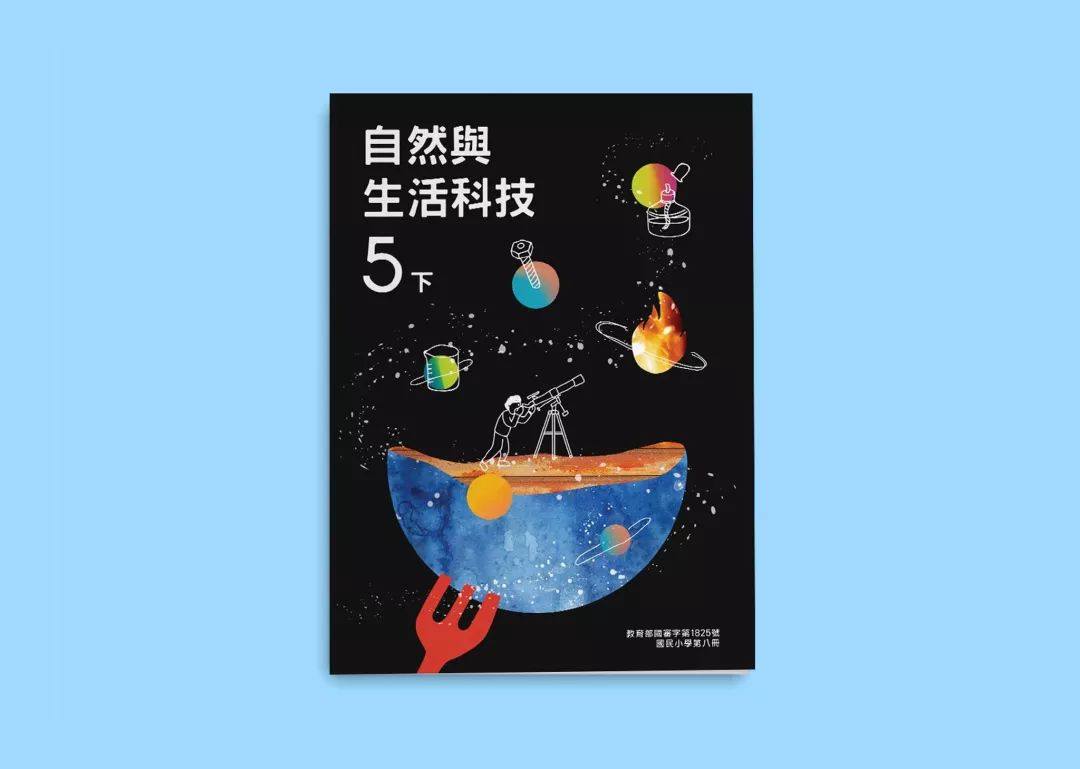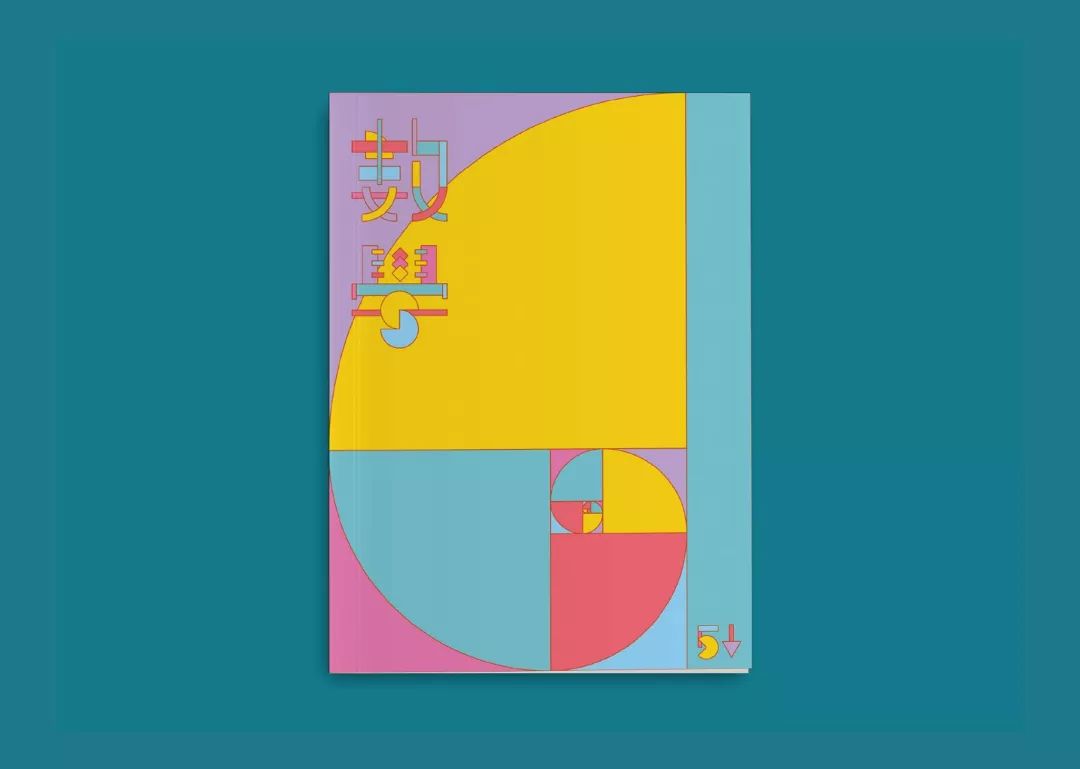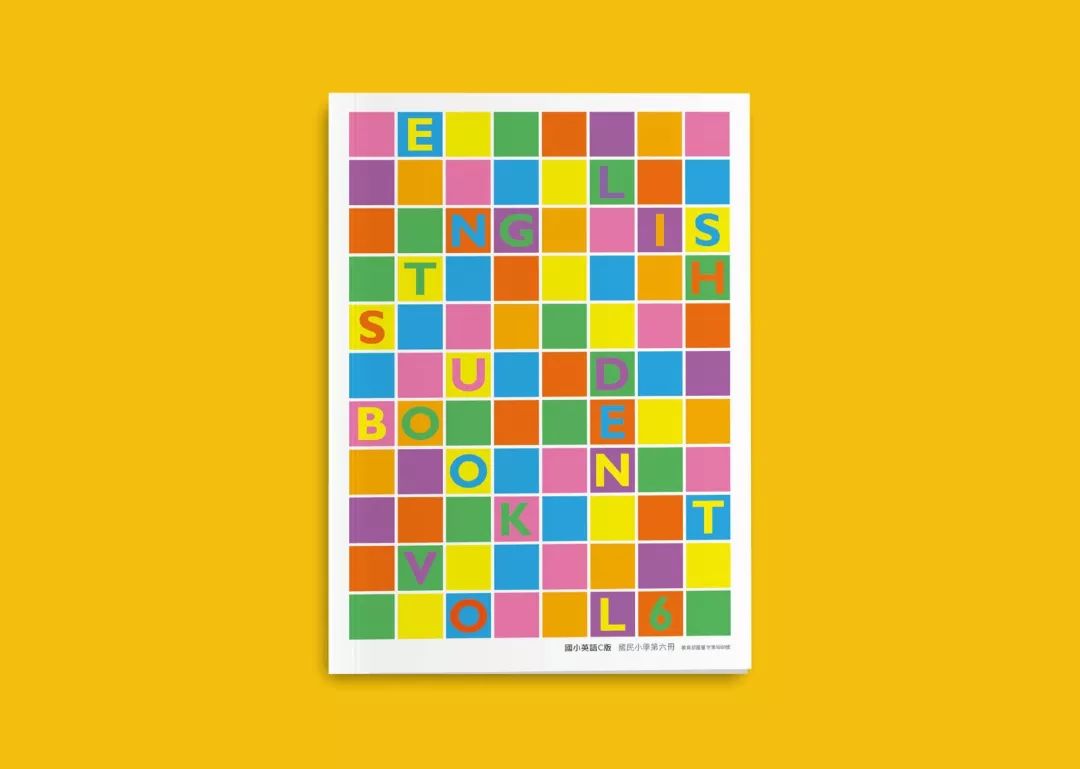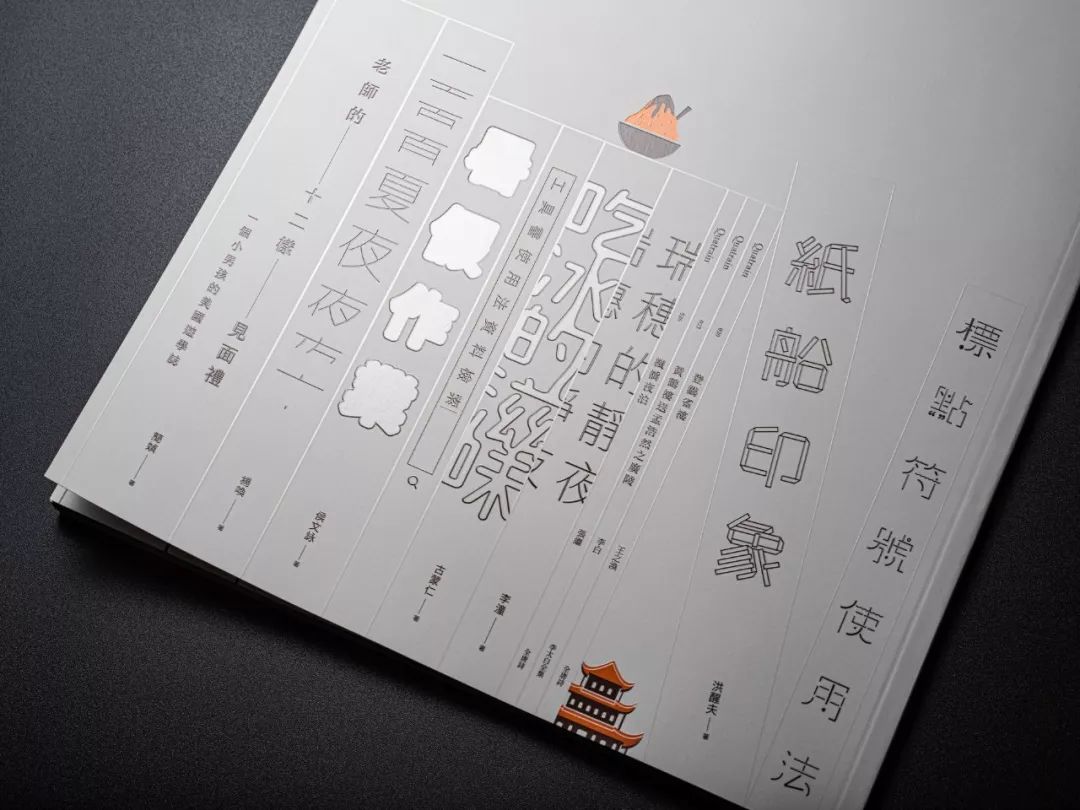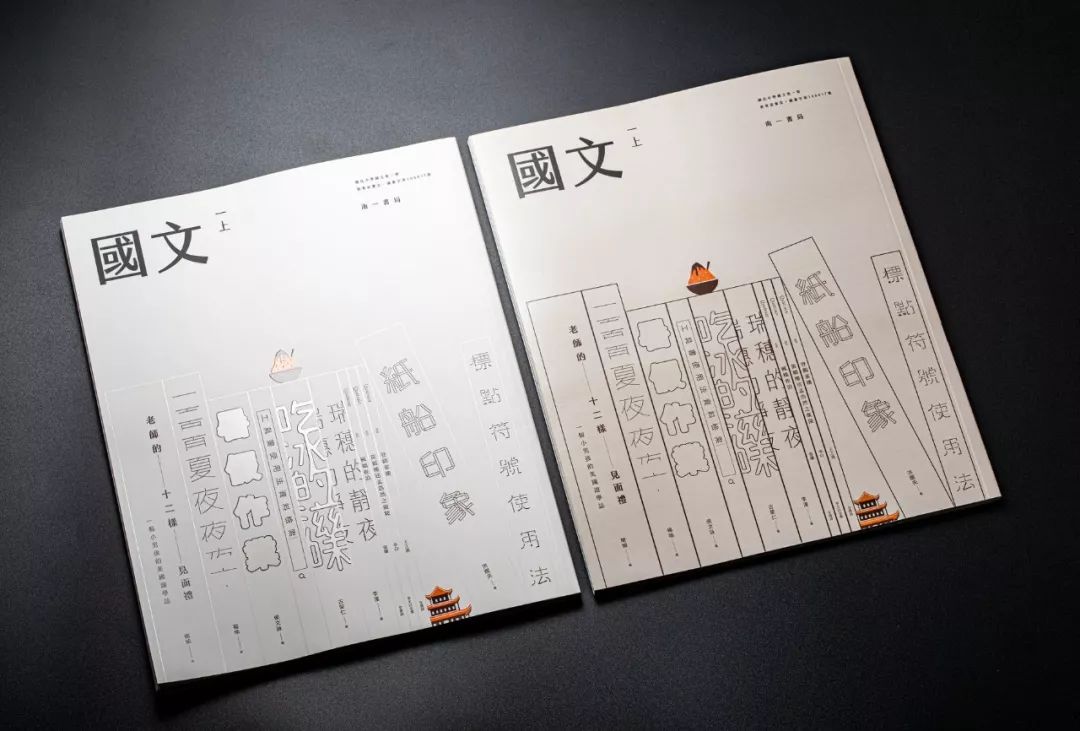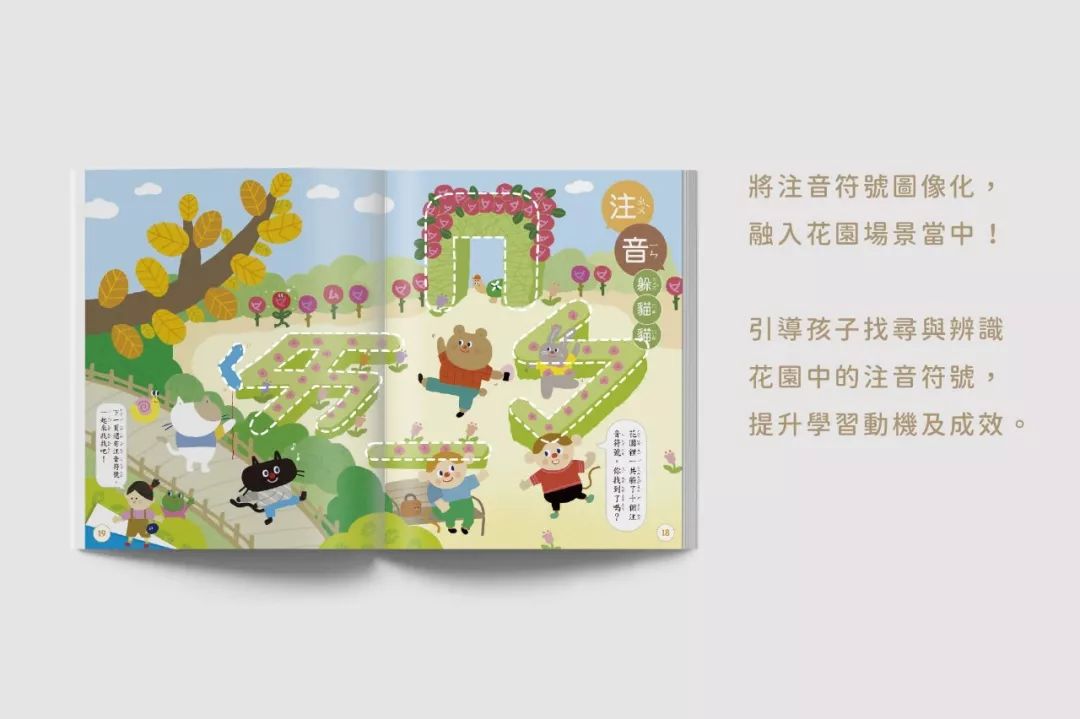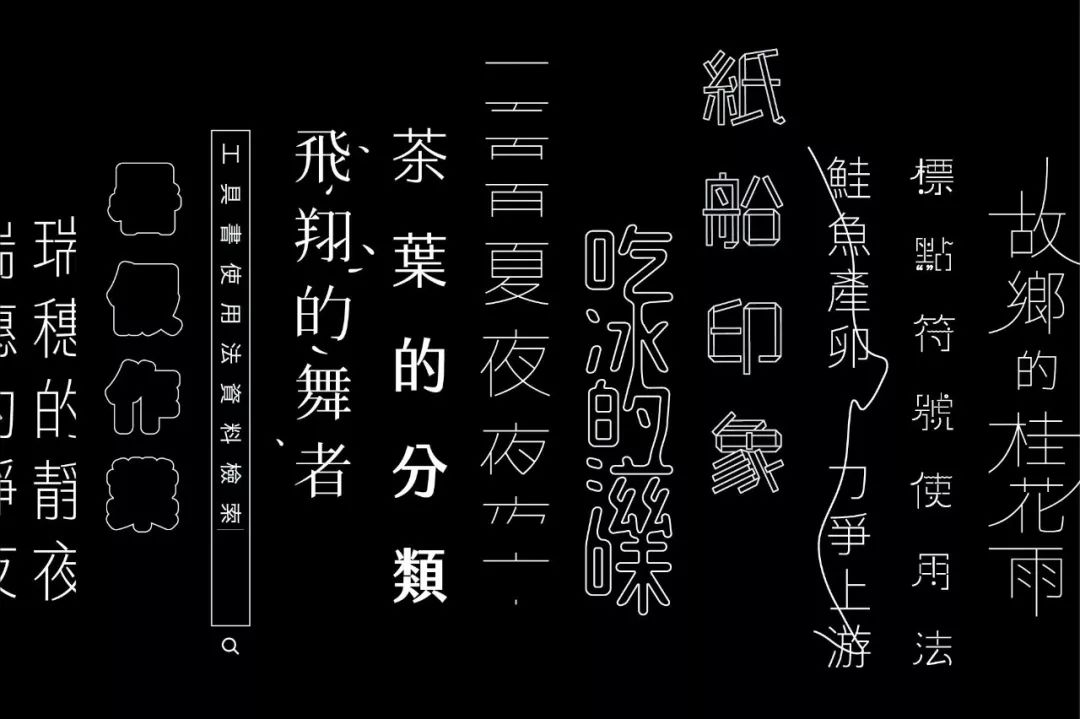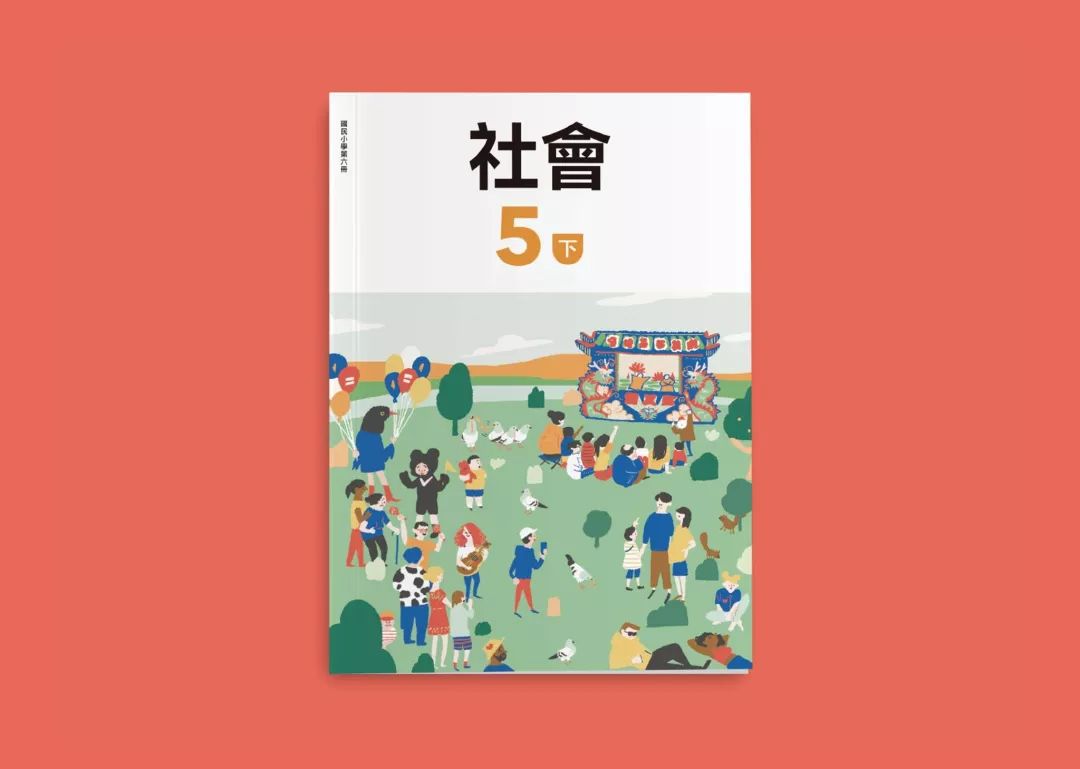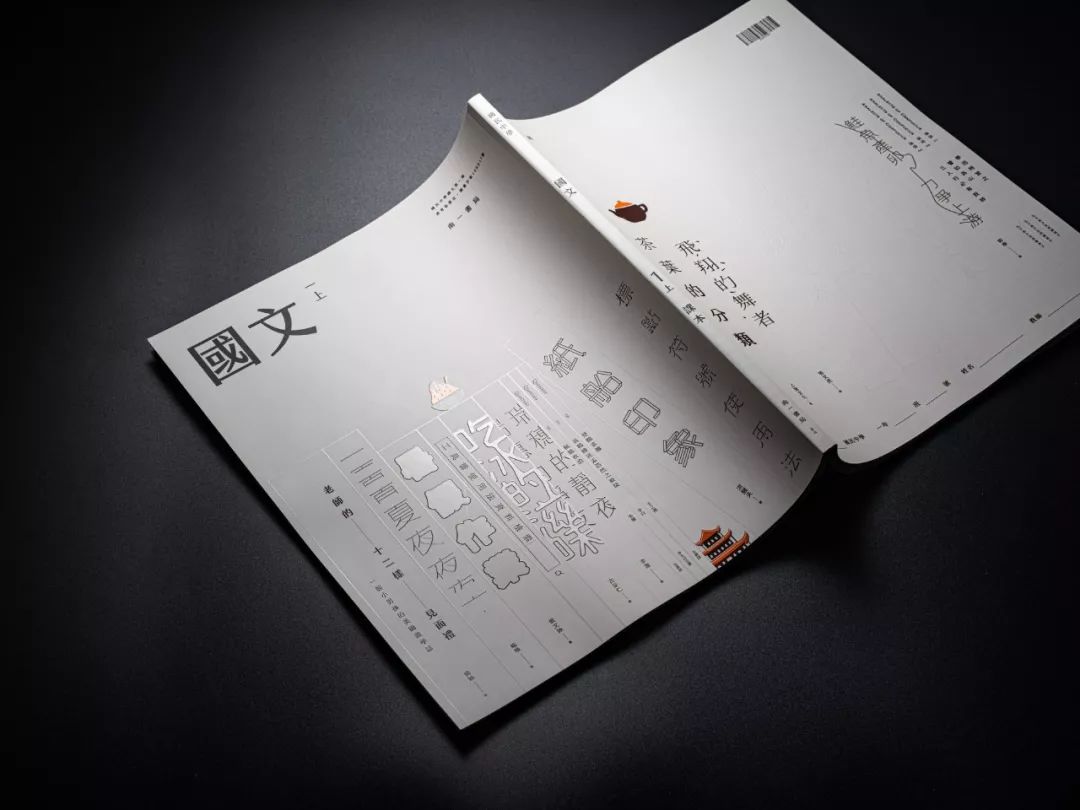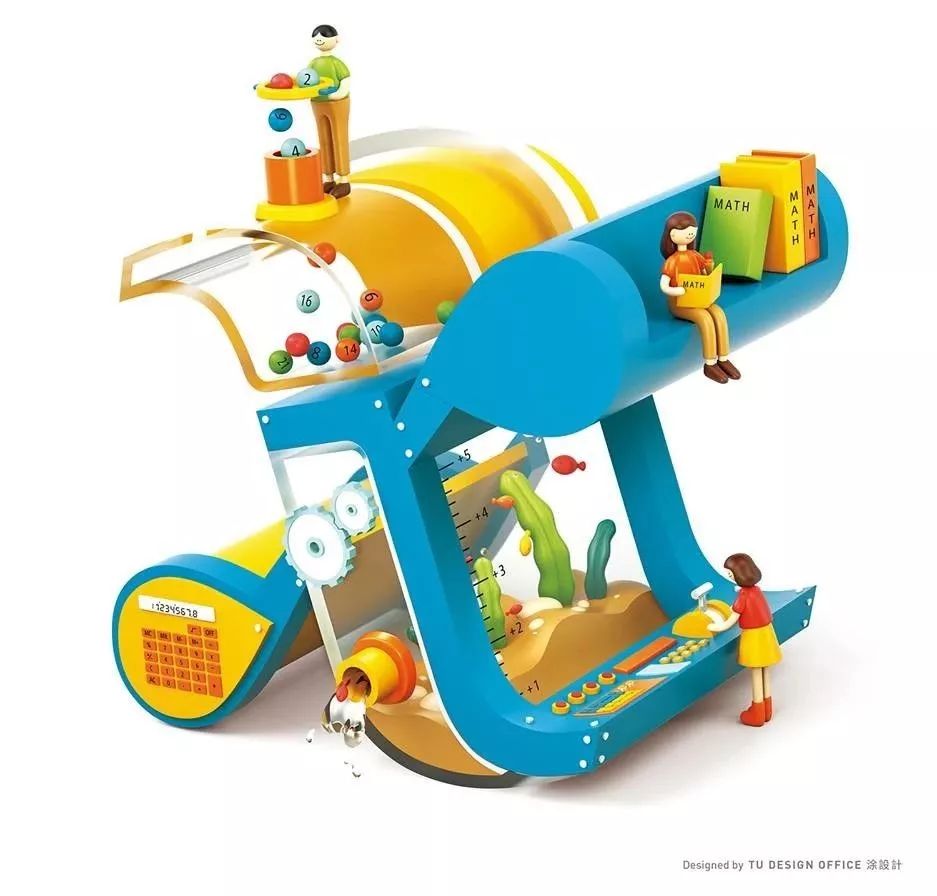
如果教科书都设计成这样,我能保送北大!
在我们的印象里
“教科书”基本上和“美”是搭不上边的
因为它要不是长这样
就是长这样
内页也和封面的画风保持统一
毫无惊喜和新意
然而,就在两年前
台湾的一套教科书横空出世
直接获得了2017德国红点设计大奖
名字也很特别
叫“美感教科书”
数学书竟然比画报还好看
你敢相信吗?!
每个英文字母都被藏在了小格子里
一般人还猜不出这是“英语书”
课本的设计不仅贴合孩子的天性
还增加了启发性
比如适当的留白
空余的地方孩子可以用贴纸自由发挥
国语书的封面只有简简单单一个笔画
可不是设计师偷懒
而是想看学生通过这一“横”
能联想起学过的哪些汉字
都叫“美感教科书”了
必然不能“徒有其表”
翻开内页
跟电影的主视觉设计也有的一拼
设计师还贴心地加了折页设计
上节课老师讲到哪儿
一翻就能找到
日站君看了忍不住想说
我当年要是有这样的课本
成绩肯定会比现在好啊!
今年,他们又杀回来了!
“美感教科书”来到第三季
观感怎么说呢
比上一季又上升了一个level吧
初一(上)的数学书
主角是个大大的代数符号“x”
别小瞧了这个“x”
里面大有乾坤
未知数x是初中数学的重要内容就不用说了
你再放大点看
左上角的小人不是在玩普通的球
而是“用筛检法找质数”
右下角水族箱上的刻度
是帮你认清“正整数”的概念
还有左下角的计算器使用
全是这本书的内容
谁看了不说一句:
设计师用心良苦啊!
这还只是个开头
下面有的你惊艳的
语文书
封面用了“书柜”的创意
每篇文章都变成了一本书
书名就是课文名
字体、大小各不相同的书本
或斜或正地摆放
你别说,还真有点书柜的意思
在做封面之余
又有了目录的功能
最妙的一点是
“书本”之间不是用不同的颜色相隔的
而是全靠凸起的外框线
也就是说,在视觉之外
语文书还有触觉上的特殊体验
“质感”满分了~
自然科学书
据说灵感来源于“连连看”
翻开课本的内页
日站君头一次发现
显微镜下的细胞竟然可以这么美!
他们甚至还邀请知名插画师Croter
在每章开头画“生活情境小漫画”
孩子在不经意间
就开始思考这章节的问题了
为设计师的机智点赞!
“枯燥”的初中教科书都能设计出花来
小学课本就更不在话下了
妥妥的“绘本风”
幽默诙谐的插画里还藏了各种“游戏梗”
猜谜
找线索
故事引导
上课还真的成了一件有趣的事儿!
“美感教科书”的企划2013年就开始了
令人没想到的是
发起人竟然是三个毫无设计背景的理工男
他们去欧洲学习时
被那边随处可见的古建筑
和浸透在日常生活中的艺术熏陶给震惊了
以至于回台湾后感受到不小的落差
“就好比,我们从小到大看习惯的公交车广告牌、小区电梯里贴的广告,那些花花绿绿的色彩组合,或者完全没有美感的醒目的大字,我们感觉是非常正常的,它原本不就是这样吗?”
那时他们才意识到
环境对一个人审美品味的影响
是下意识的、又是决定性的
但这好像不是多开几个博物馆、艺术展
就能解决的
怎么办呢?
于是他们想到了教科书
一个孩子在12年义务教育下
花在课本上的时间约为12760个小时
相当于看6000部电影
去3000次美术馆
如果课本不再只传达知识
还能兼具美的熏陶
那12年后
有没有可能影响一代人的美感呢?
所以他们邀请了13名设计师和插画家
对教科书重新改造和排版
让孩子从小耳濡目染用心的配色、线条、插画
打造一个美的环境
他们的口号是
“给我们一本课本,我们给孩子一座图书馆”
“美感教科书”的发起人曾说
美感教育的重点不是“美”,而是“感”
是培养自己对美的感受、想法和观点
所以与其告诉孩子什么是“美”
不如给他们提供更多风格的课本
激起他们对美的热情
让他们知道,“美”有很多种不同的方式和可能
希望有一天
大陆也能拥有这样的教科书
让孩子在学习课本知识的同时
还能接受美的教育